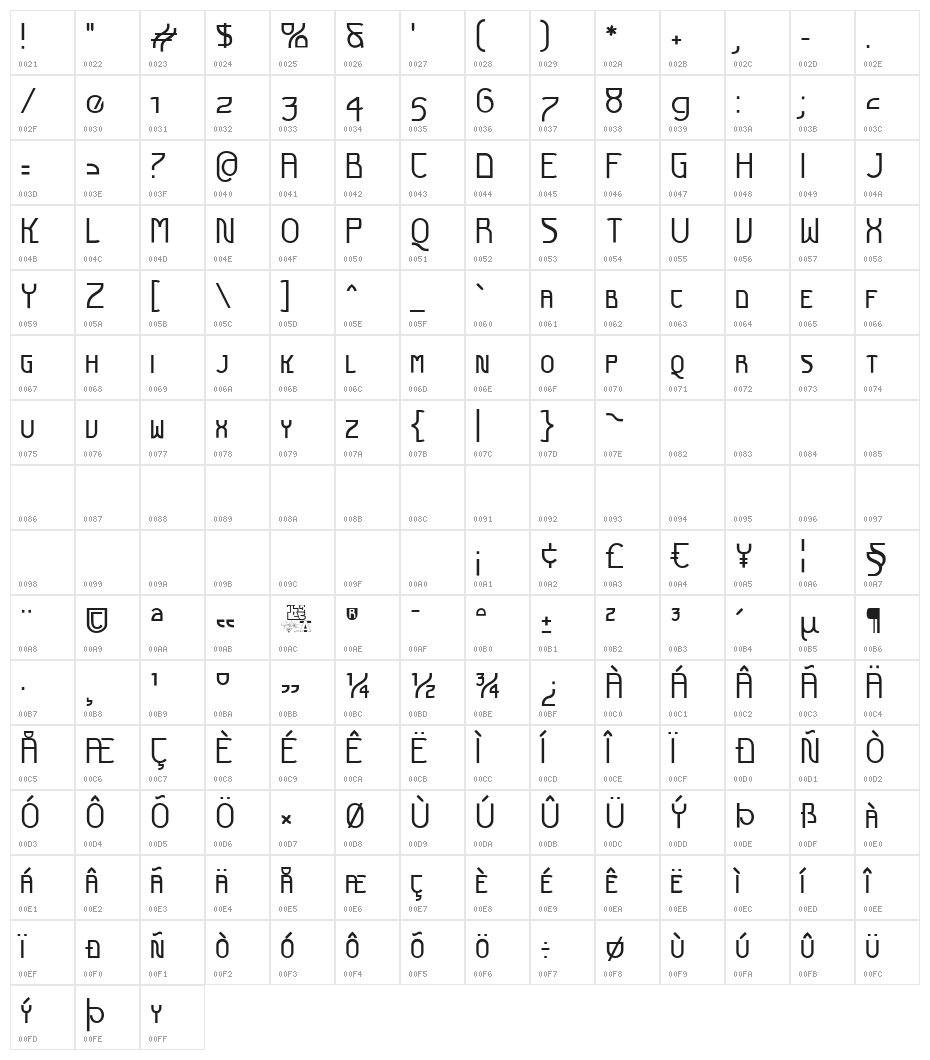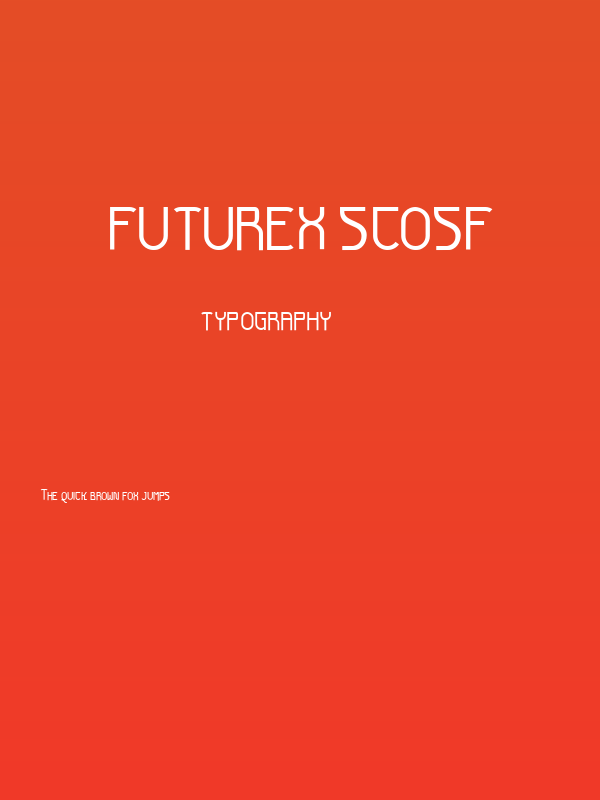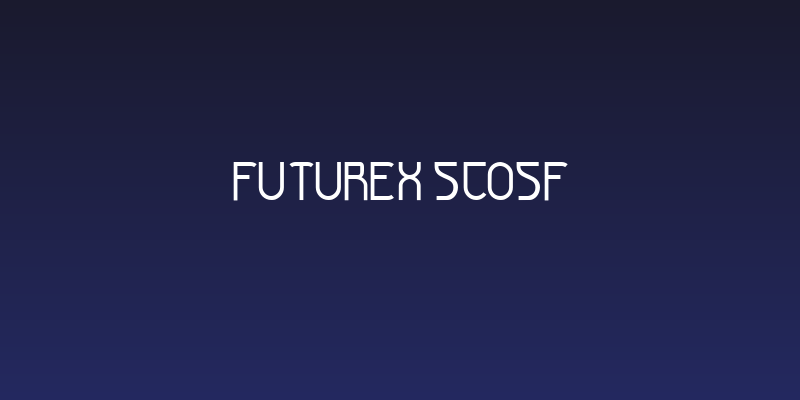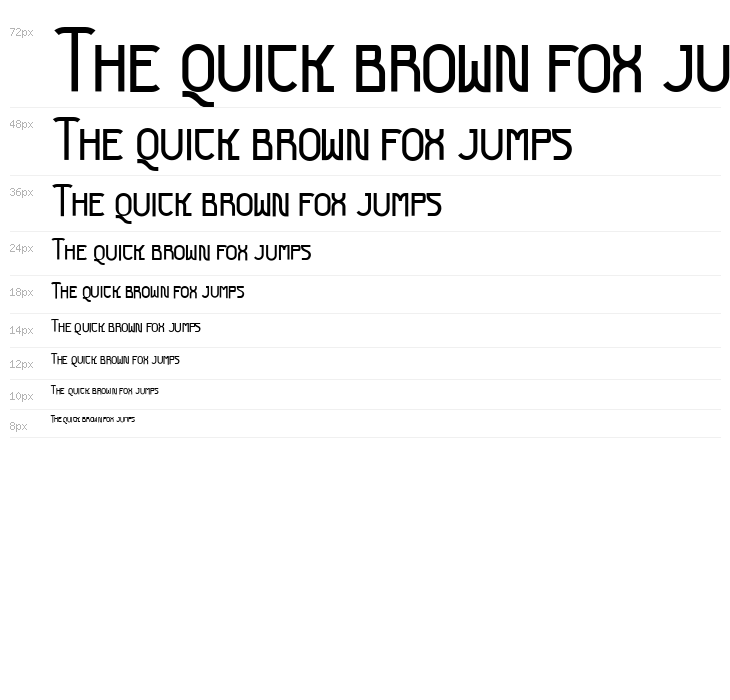
Futurex SCOSF Font
| Caso d'uso | Headlines, Logos, Digital interfaces |
| Progetti proposti | Ideal for technology branding, sci-fi themed designs, modern advertising, and digital interfaces. |